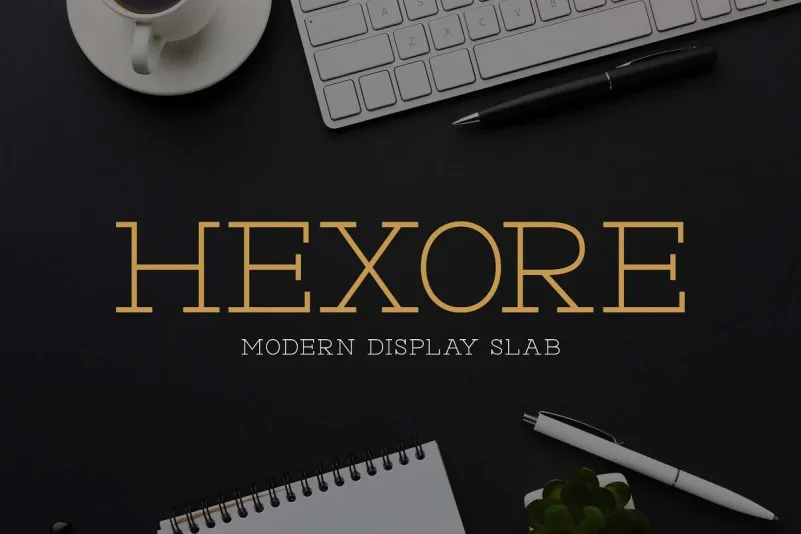
A Hexore Font é uma elegante escolha para aqueles buscando um estilo de tipo slab serif que traz consigo tanto sofisticação quanto simplicidade. Desenvolvida pela Almarkha Type, essa tipografia incorpora os elementos clássicos e modernos do tipo slab serif, oferecendo uma combinação única que impressionará seus leitores em qualquer projeto gráfico. Inspirada nos famosos logotipos minimalistas, a Hexore é perfeita para a criação de templates, brochuras, vídeos, marca de publicidade e até mesmo para design de logos. Seja você um profissional ou iniciante, essa fonte é versátil o suficiente para moldar qualquer projeto em sua favor, garantindo uma estética arrojada que se adapta perfeitamente a diversos ambientes de trabalho.